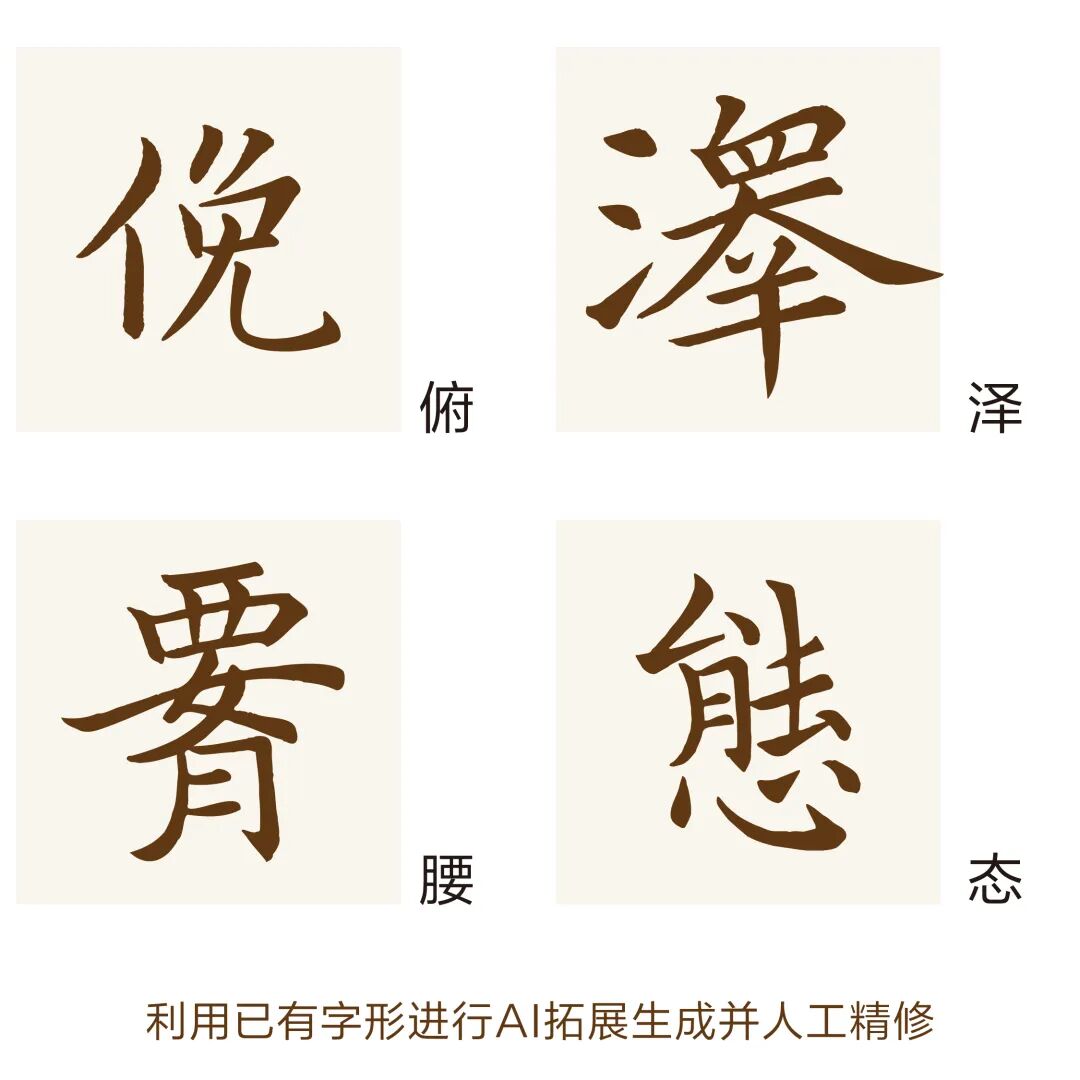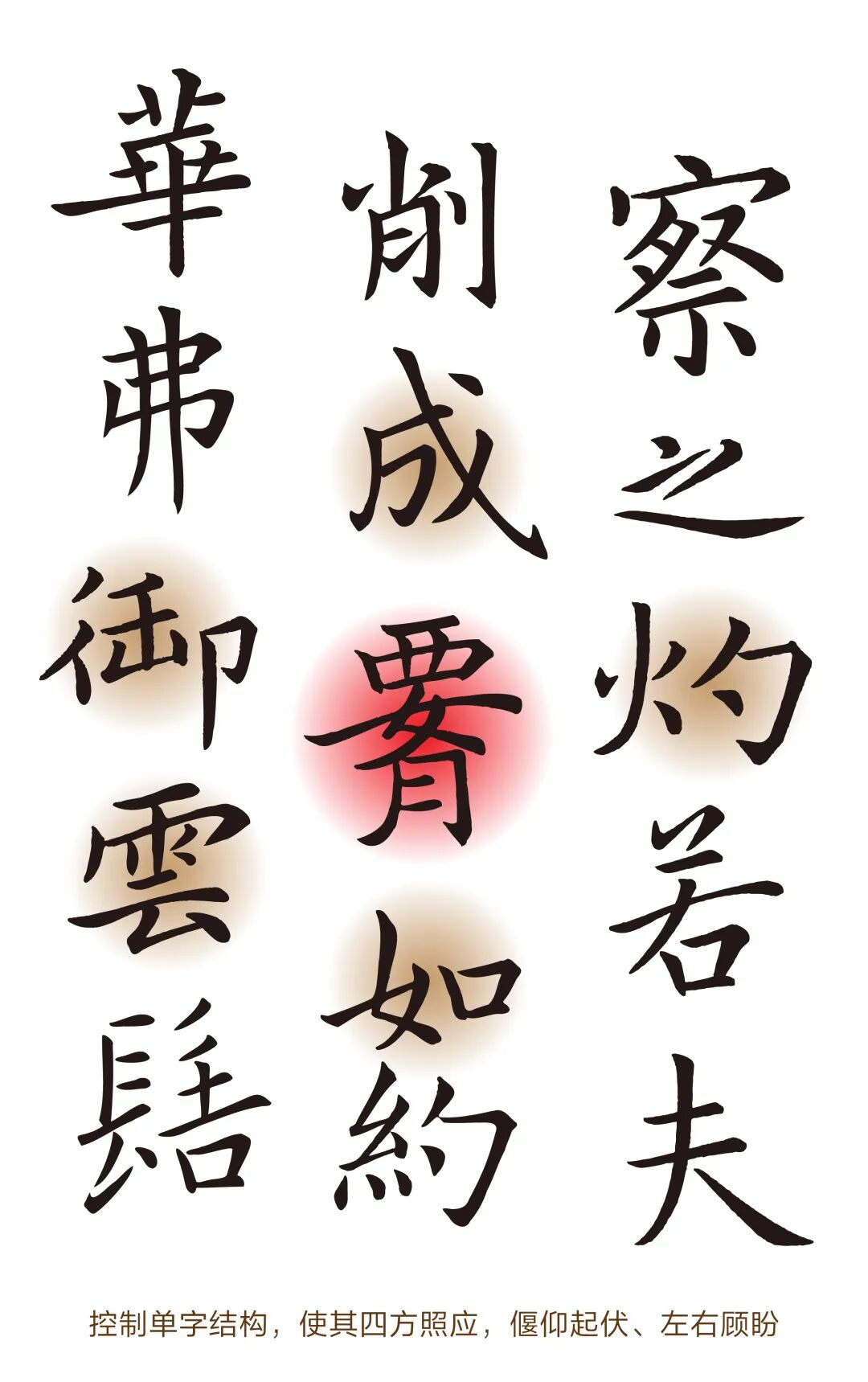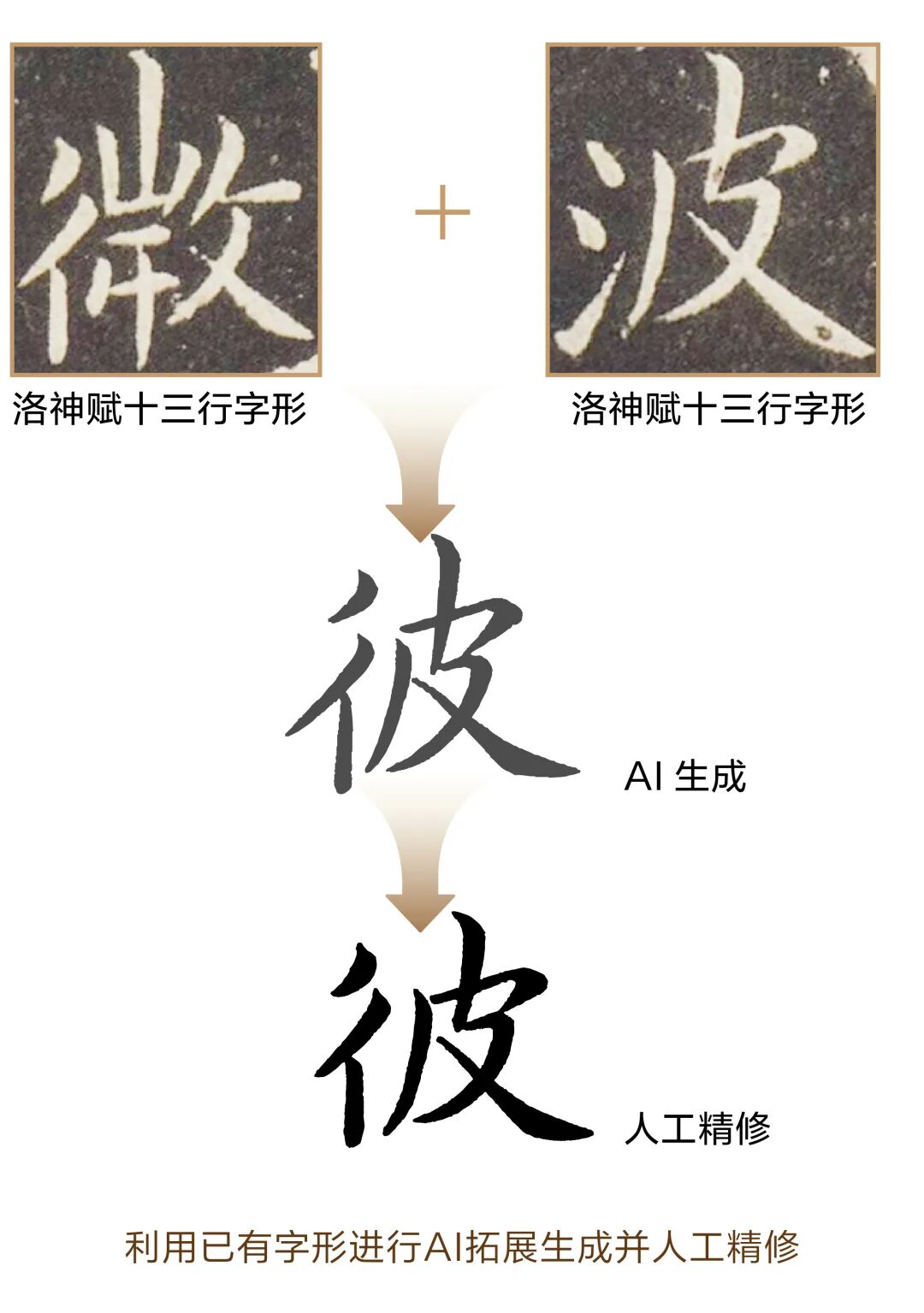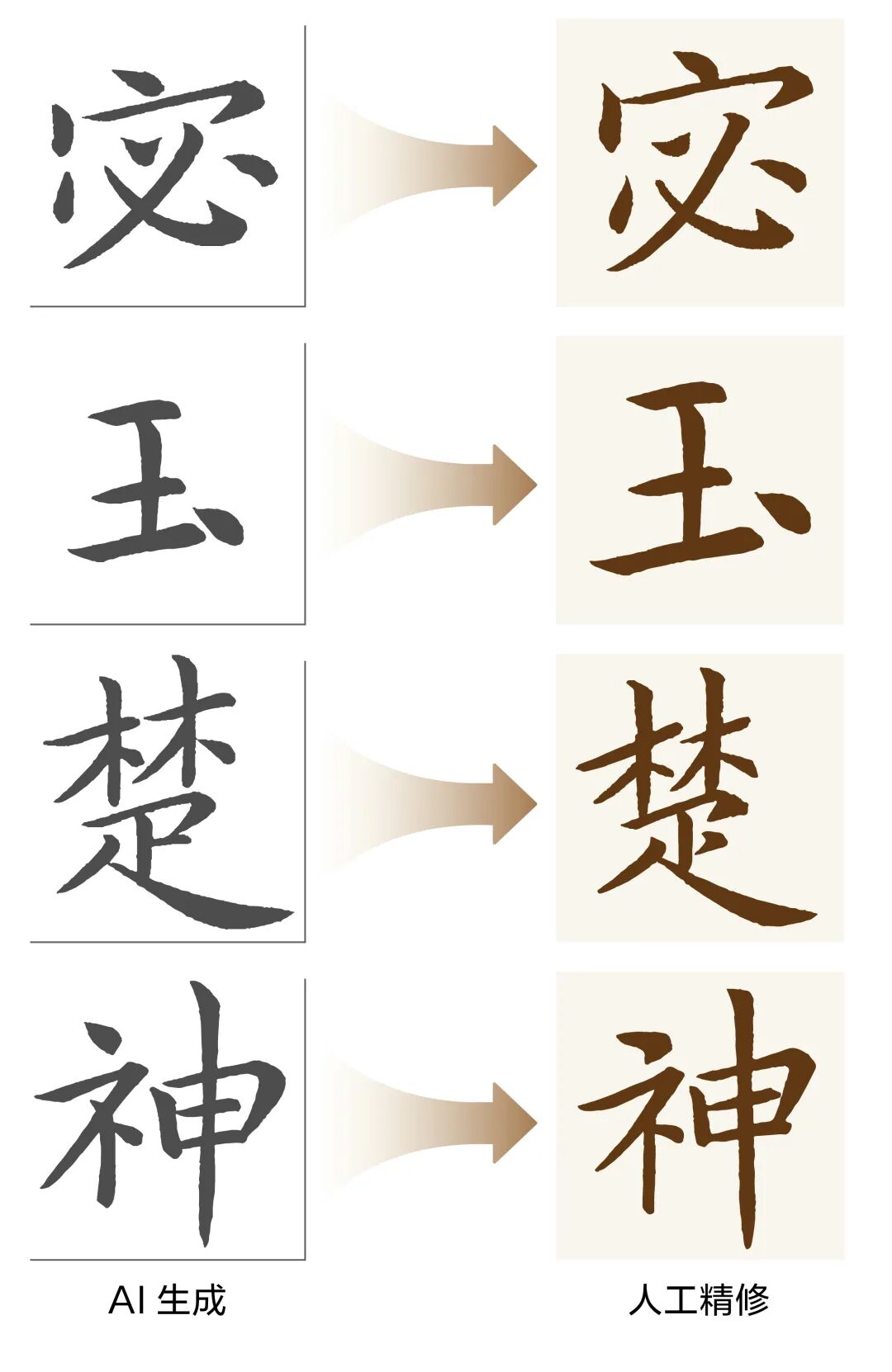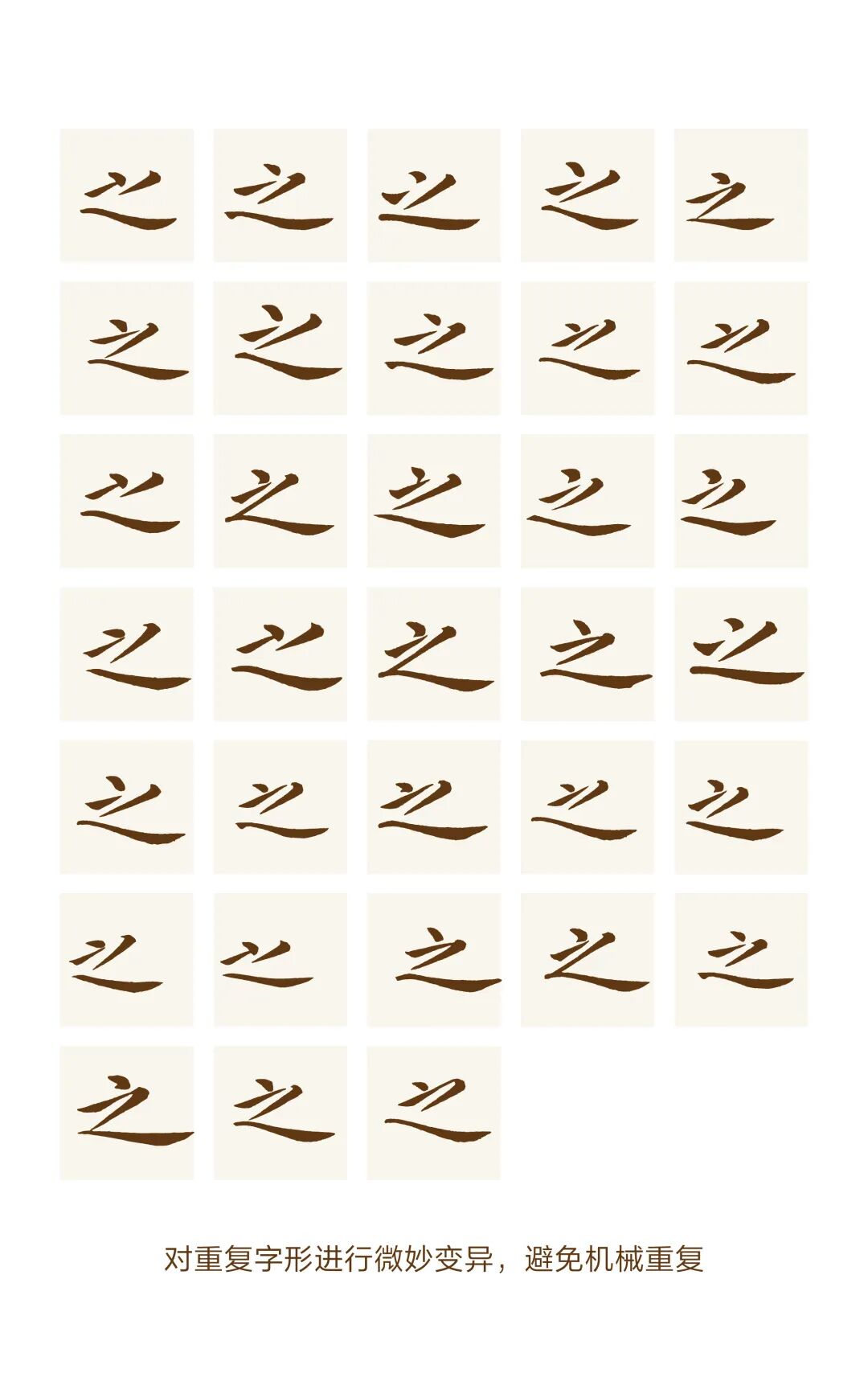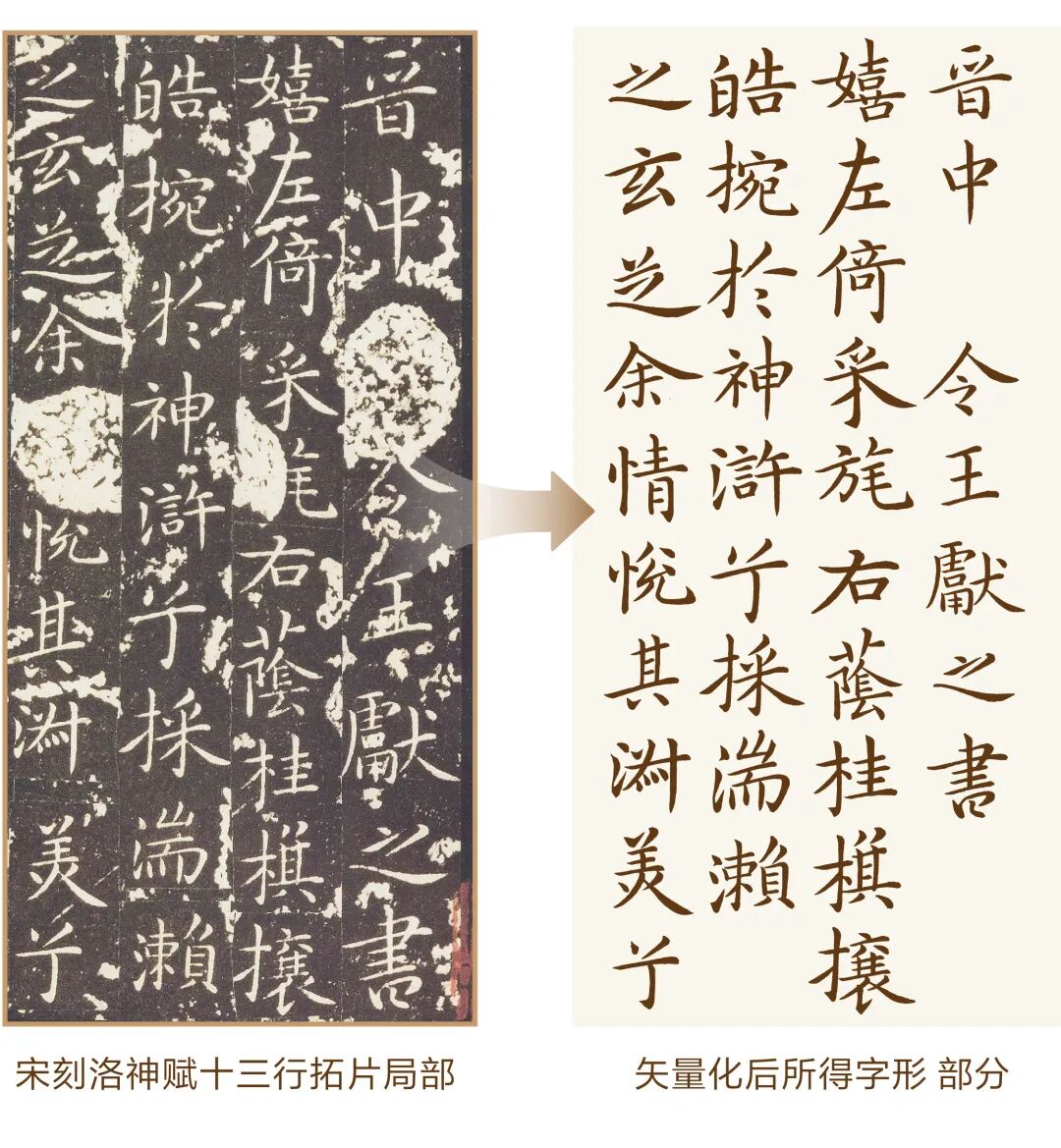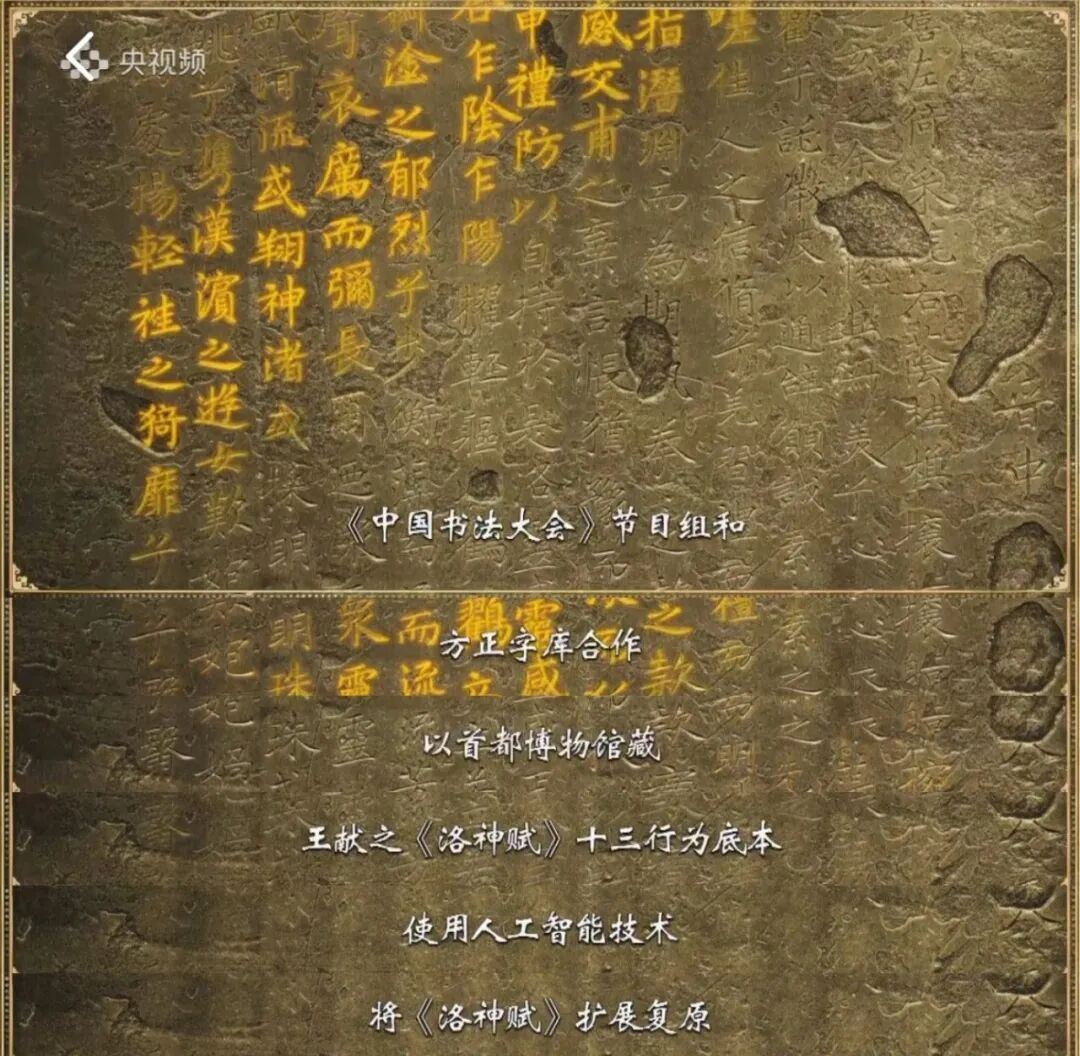
当魏晋笔锋邂逅数字技术,一场跨越千年的书法重生正在荧屏上演。2025年8月13日,《中国书法大会》第二季第三集正式播出,以破壁之姿揭开文化传承新篇章:节目组携手方正字库,以仅存约250字的王献之“玉版十三行"残卷为基础,借助方正字库专业的书法字体设计能力以及先进的AI造字技术,成功复原失传千载的919字《洛神赋》全卷。
“怀虔诚之心,以科技之力,向书法经典致敬”,《中国书法大会》与方正字库的专家团队,以敬畏之心突破三大技术与艺术壁垒,让数字时代的笔墨与魏晋风骨完成了一场跨时空对话,成功再现“碧玉”之作,向古人致以跨越时空的敬意,也让更多的人能够领略到这一艺术珍品的魅力。
三国烟云间,曹植以“翩若惊鸿,婉若游龙”的绝妙意象,铸就中国文学史上一曲经典的人神恋歌。东晋书法家王献之对这篇作品情有独钟,常常以其为书写素材,笔锋起落间,文学意境与书法美学达成完美共振。
王献之墨本《洛神赋》以隽秀挺拨的笔划、萧散逸岩的结体,树立了小楷艺术的巅峰标杆,被誉为“小楷极则”。其字字顾盼生姿的布局,将曹植文字中的缠绵情致转化为可视化的空间韵律,成就“一帖双绝”的文化奇观。然而,经过岁月淘洗,王献之书《洛神赋》的真迹在唐代已然破损散佚,唯余十三行约二百五十字,从“嬉”字起至“飞”字止,如同断臂维纳斯般令人既惊叹又惋惜。
当数字时代的科技之光照见千年残石,一项前所未有的挑战浮现:如何让仅存不到三成的王献之《洛神赋十三行》重构完整神韵?这不仅是对字体复原技术的考验,更是对魏晋风骨与书法气韵的跨时空解谜。
面对这一复原难题,《中国书法大会》选择与方正字库一同开启这场跨越时空的书法对话,这也是继王羲之行书之后双方的再度合作:以残存约250个字的《玉版十三行》为底本,借助方正字库专业的书法字体设计能力及AI造字技术的支持,力求还原王献之当年所写的919个字的《洛神赋》原貌。
本次《玉版十三行》的还原过程中,设计师采取了全新的「AI+书法」双轨并进设计思路:既要攻克历史底本的多重迷雾,又需在缺失的字中延续王献之「简静秀润、顾盼生姿」的笔法精髓,更要破解千年章法的空间密码。这场融合文献考据、智能技术与艺术造诣的攻坚,不仅是对书法基因的解码,更是数字时代对文化传承的深度致敬。
在宋元时期,《洛神赋十三行》墨迹有晋麻笺本和唐硬黄纸本流传。如今备受推崇的宋刻“碧玉版”(《玉版十三行》),疑为南宋贾似道据麻笺本翻刻,堪称现存最精版本。深入研究此版本,有助于我们理解王献之艺术风格与古代文人情感思想。
此次复刻还原王献之《洛神赋十三行》(碧玉版),方正字库设计师与《中国书法大会》节目组煞费苦心。经商议,以首都博物馆藏的“碧玉版”为主要底本,并参考《宋刻玉版十三行佳拓》等珍贵拓本。这样的选择不仅确保了书帖的历史真实性,还能更加准确地把握王献之的书法特点,力求尽量还原其当年的书写风貌。
确定底本后,难题接踵而至,原石中部分字形残缺,这给复刻带来极大挑战。对此,设计师首先借助AI技术对底本文件进行增强处理,得到更清晰可辨的字形,再以此为依据逐字勾勒出矢量化字形。最后将复刻字体嵌入原石,逐一进行比对和调整。
对于原石中有残缺的字形,设计师凭借着多年积累的书法造诣和对书法艺术的深刻理解,对残缺字形的比例、结构、走势等进行精准填补及修正,巧妙减小了传拓过程中可能存在的失真问题所带来的影响,让这部经典之作以更接近原貌的姿态重现。
由于《洛神赋十三行》(碧玉版)仅残存约250字,要还原出919个字的《洛神赋》原貌,则必须对缺失的字进行补字。在这一过程中,设计师主要用到了3种方法:一是搜寻并复刻现仍留存于世的王献之其他手迹中的小楷字形;二是参考“二王”一脉具有相同小楷书写风格的书家之作进行复刻;三是利用AI造字技术,基于已有字形,对所需字形进行仿写拓展。
方正字库AI智能生成字体技术中的仿写拓展技术,可以通过分析现有字体的特征,仿写并拓展这些字体的风格和样式。设计师将从《洛神赋十三行》中提炼出来的复刻字交给AI技术团队,通过AI大模型进行字形风格抓取,快速生成了其余汉字。通过AI生成的字形,已经能基本满足常规书法字库的使用需求,但对于《洛神赋》这样一件艺术作品来说,还需由字体设计师进行逐字精细化调整,确保成果忠实反映王献之书法艺术的精髓。
在《洛神赋十三行》(碧玉版)复刻及AI补字基础上,补字采用古汉字异体字写法,还原其用笔方式。此外,为避免字库字体的弊端,设计师在同一个字的书写中,依据全篇结构和文字位置探索了不同的变化,形成流畅自然的书写节奏 。
在《洛神赋十三行》数字化复原过程中,章法气韵的还原是一大挑战。方正字库设计师依托深厚的书法功底,将原帖章法气韵精准注入数字排版。通过精微观察原石残迹,系统解构王献之小楷的布白规律与节奏韵律:从单字造型到行气呼应,从笔画轻重到虚实疏密,每一处细节都经过缜密推敲。
设计师首先将章法意识贯穿于每个单字的创作中:既考量单字的收放、重心与姿态,更预判其融入整体篇章后的空间关系。通过调控字形大小、行距疏密与笔画疾涩变化,在二维平面重构出原作流动的呼吸感。面对高频虚词重复难题,巧妙运用“同字异构”的传统智慧,对“之”“而”等字进行笔意微调,既保持原帖精髓又破除机械感,实现“变而守法”的艺术平衡。
在分间布白层面,设计师精准还原魏晋小楷特有的空间美学:通过字间偃仰顾盼的节奏把控,使疏朗处若星汉散落,紧密处似珠玉叠映。最终还原出全篇自然天成的章法之美,让经典以数字化形式重焕生机。
当这幅凝聚着智慧与技术的数字《洛神赋》全卷最终呈现时,节目组三位点评嘉宾对其复原成果产生强烈共鸣,并一致给予极高评价。浙江大学教授薛龙春表示:“做得真是让我吃惊,做到这个程度,确实出乎意料,尤其是对字形整体的把握,与王献之的《玉版十三行》相当接近。”
清华大学美术学院博士生导师邱才桢赞叹道效果“非常震撼”,他对比道:“之前看的石刻《玉版十三行》拓片因为是黑白的,显得朦胧缥缈,而且有一种悠远的朦胧感,就像旧照片上的美女;但是这件作品的话,就像刚才看到过的,那群美女在群舞,婀娜多姿,摇曳生姿,非常漂亮。”
中山大学教授彭玉平则用“叹为观止”概括他的感受:“我自从学了‘叹为观止’这个成语,我一直不知道用在哪里,我今天找到了用的地方,这是我的第一个感受,第二个感受来说,我就觉得科技我一直觉得它是冷冰冰的,我第一次感受到科技居然给我带来了如此亲切而且温暖的感觉。”
在还原王献之《洛神赋十三行》全篇书帖的过程中,方正字库运用自主研发的AI辅助造字技术,帮助设计师显著提升书法作品还原的精度与效率。
方正字库的AI辅助造字技术在此次王献之《洛神赋十三行》书帖的还原中得到了深度应用,通过对原版约250个汉字的风格抓取和学习,AI能够快速智能地生成待补汉字,使得补充的字形在风格上与现存部分相协调。最终,由设计师对每个字进行精细化的逐字调整,确保最终成果能够忠实反映王献之书法艺术的精髓。
如在“中华精品字库工程”开发项目中,方正字库利用人工智能技术辅助设计师高效实现碑帖切字识别,迅速且精准地处理大量书法作品;支持在书法家根据原书法风格仿写的2000个汉字基础上进行风格抓取,快速生成其余汉字,然后由字体设计师进行调整,力求还原书法艺术的造型风格与精神内核,同时满足现代汉字的应用需求。
书法作为中华文明千年传承的文化瑰宝,承载着深厚的历史与艺术价值。《中国书法大会》第二季通过数字技术与人文智慧的创新融合,让历史长河中的书法经典焕发新生。方正字库团队携手节目组,通过书法字体设计与人工智能技术的大胆结合,对王献之《洛神赋十三行》全卷进行了精心复刻,让散佚于历史长河中的书法经典穿越时空,与现代观众重新相遇。
这场跨越时空的艺术对话,既是对散落历史遗珍的系统还原,更是以创新思维激活传统文化生命力的生动实践,方正字库以「AI+书法」的积极应用,为进一步推动中华书法文化的传播与发展提供新的可能!
大型文化节目《中国书法大会第二季》由中央广播电视总台与中国书法家协会合作推出。节目聚焦河南安阳殷墟、陕西宝鸡周原、山东曲阜孔庙、河南洛阳龙门石窟、陕西西安碑林、甘肃敦煌六大书法胜地的18组极具代表性的中国书法作品,通过知名专家讲解、穿越式情景演绎、现场互动和VR、AR、AI等科技手段,打造一场别开生面的书法文化盛宴,探寻中华文化的深厚根脉,在笔墨渲染间感受中国文化的源远流长。